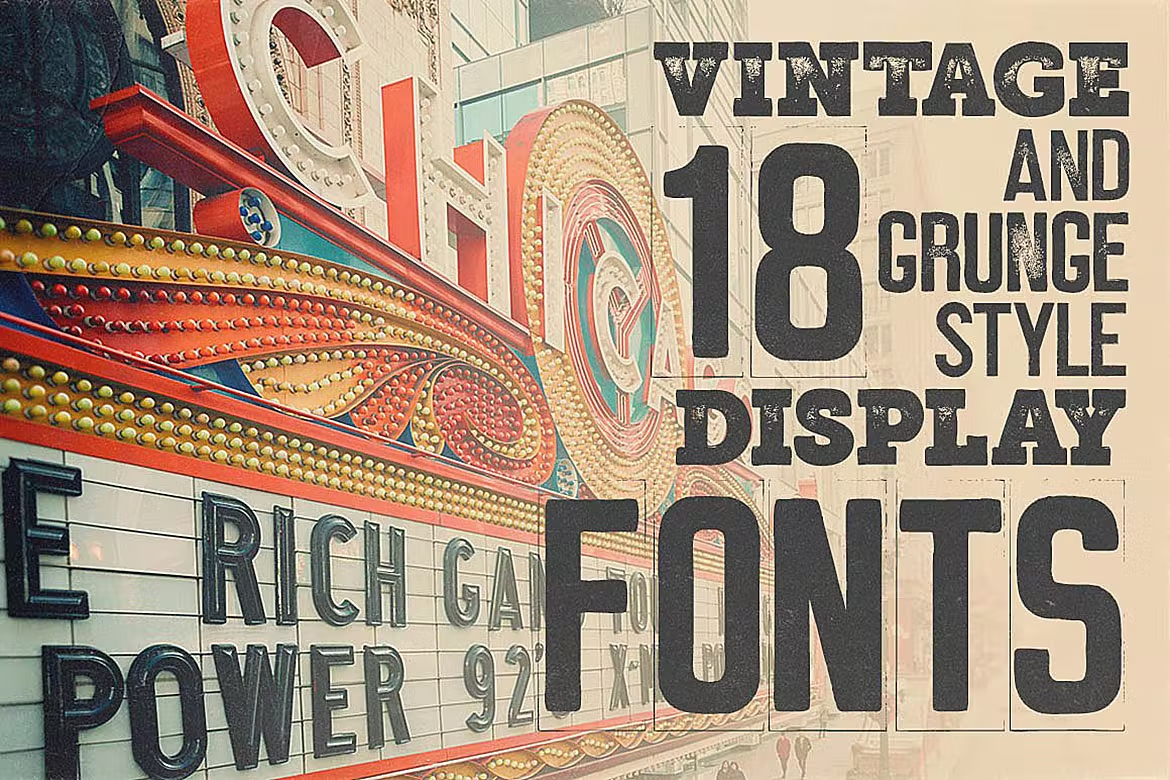
Marquee 18 Grunge Font
Vous trouverez 18 polices d’affichage de style grunge dans cet ensemble – donc si vous n’avez besoin que de polices grunge, cet ensemble est fait pour vous